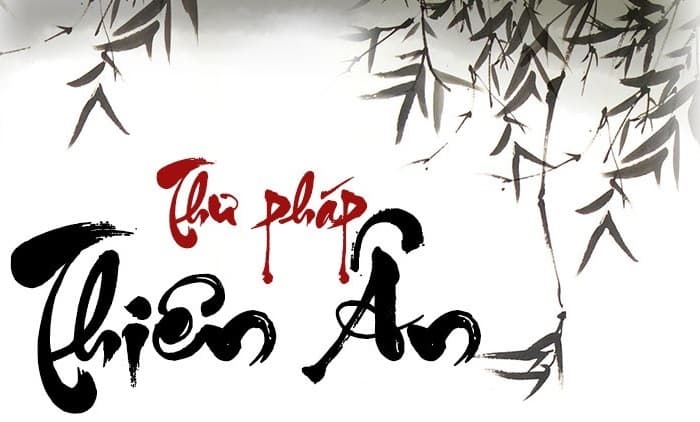
Font thư pháp hay các nhiều người còn có tên gọi là font ông đồ là những phông chữ với nét chữ làm khác lạ. Đặc sắc, dấu ấn cho khán giả cảm nhận như rồng bay phượng múa đầy nghệ thuật. Bởi thế font thư pháp được sử dụng vô số trong những sản phẩm thiết kế. Trong thể hiện tài liệu, thiệp chúc mừng, … Những người nên dùng font thư pháp để thiết kế nên những sản phẩm nghệ thuật siêu đẹp và nổi bật.
Font thư pháp là gì ?
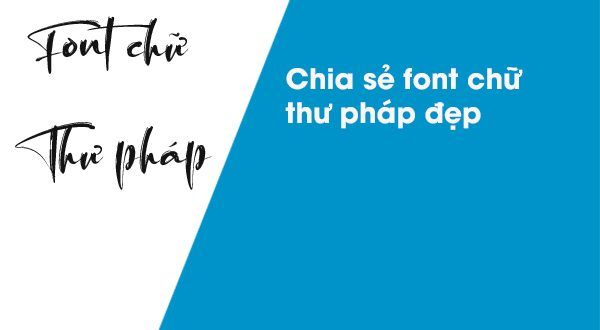
Mọi người còn gọi font thư pháp là tổng hợp các phông chữ với các nét dày mảnh sự khác nhau. Được làm ra bởi các nét mực y như lúc dùng bút mực đề dòng chữ lên giấy mà các ông đồ vẫn thường làm. Hiển thị lên tài liệu trông rất nghệ thuật không thể phủ định là như rồng bay phương múa.
Dẫu vậy, phông chữ này không phù hợp với các tài liệu cần đọc nhanh. Mà chỉ thường được ứng dụng lúc muốn tạo ra những sản phẩm nghệ thuật thích mắt.
Hiện font thư pháp phân phối hàng chục phông chữ đặc sắc để khách hàng quyết định. Một danh mục các phông chữ đẹp sẽ hiển thị và bạn chỉ cần dùng cho. Bất kỳ phông chữ nào cho các tài liệu đã được soạn sẵn là có khả năng biến chúng thành những định dạng chữ bất thường và đặc sắc. Tức thì với nhiều nét không giống nhau. Làm cho bạn đề dòng chữ theo nhiều kiểu trên nhiều bức ảnh, không sự trùng lặp. Bởi vậy, dùng phông chữ này để :
- Thiết kế hình ảnh
- Thiệp chúc mừng
- Bìa sách , vở …
Hẵn nhiên sẽ dẫn đến hiệu ứng tích cực.
Font Thư Pháp dễ dàng thích ứng với các bộ gõ Tiếng Việt
Font Thư Pháp hay còn gọi là font chữ ông đồ là những font chữ với nét chữ phá cách, để bạn sáng tạo nên những tác phẩm nghệ thuật độc đáo. Đây là các phông chữ True Type, gõ theo mã VNI nên dễ dàng tương thích với các bộ gõ tiếng Việt trên hệ thống. Đây là hàng trăm bộ font chữ độc đáo để bạn có thể thoải mái lựa chọn.
Các bộ Font Thư Pháp nổi tiếng như Font Thư Pháp Thiên Ân, Font Thư Pháp Công Thủy hay Font Thư Pháp Thành Công đều có tính tương thích cao, bạn có thể tham khảo.
Một số loại font chữ thư pháp nổi bật được nhiều người yêu thích
Có nhiều font thư pháp khác nhau, bạn có thể thoải mái lựa chọn font phù hợp. Để phục vụ cho công việc của mình. Dưới đây là một số font được nhiều người chọn sử dụng.
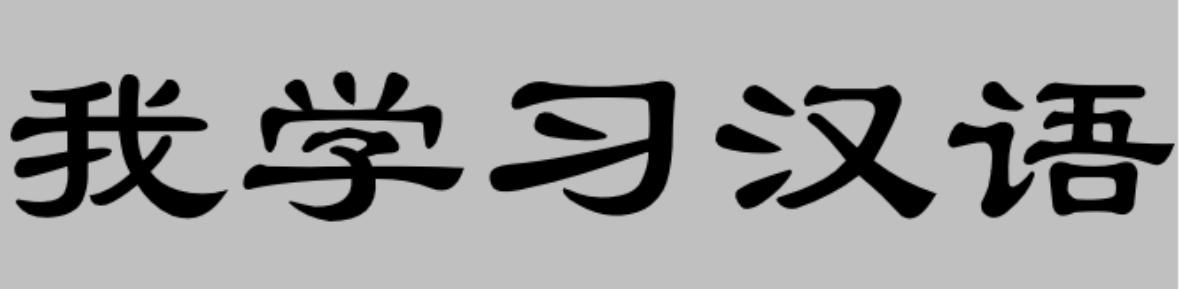
Khởi nguồn của thư pháp là từ Trung Quốc, với dạng chữ tượng hình của họ. Cho nên bộ thư pháp bằng kiểu chữ Hán (Trung Quốc) vẫn phát huy vai trò tích cực ở Việt Nam. Cũng được sử dụng trong những dịp đặc biệt như tết nguyên đán, những ngày trọng đại của gia đình, tổ tiên.
Font thư pháp Trung Quốc giúp chúng ta viết được những chữ ý nghĩa xúc tích. Bằng tiếng hán như Phúc, Lộc Thọ, Hiếu, Nhẫn, Tâm…. Nhất là đối với ai yêu thích nét đẹp trong văn hóa cổ xưa.
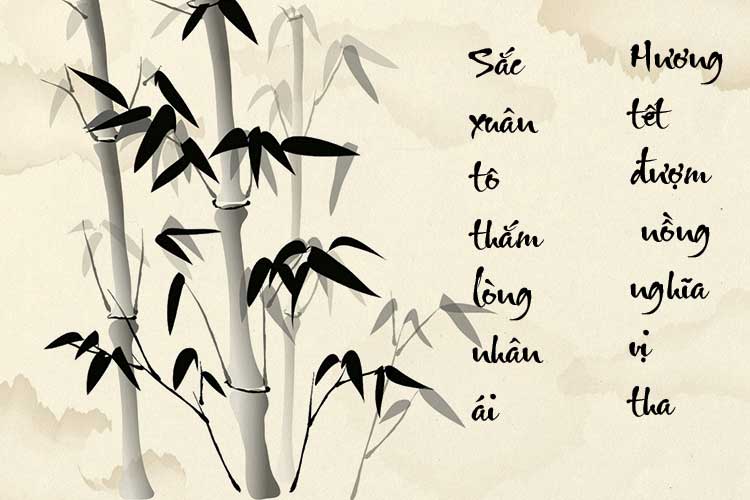
Loại Font thư pháp xuân được dùng chủ yếu trong các dịp lễ tết nguyên đán. Những mẫu thư pháp đẹp dành cho ngày xuân luôn gợi lên trong lòng chúng ta điều gì đó hứng khởi, tràn đầy sức sống tưni mới trong những ngày đầu xuân vui vẻ. Không chỉ vậy, Những nét chữ trỏng bộ thư pháp này thực sự biến bạn trở thành một ông bà đồ trẻ thực sự.